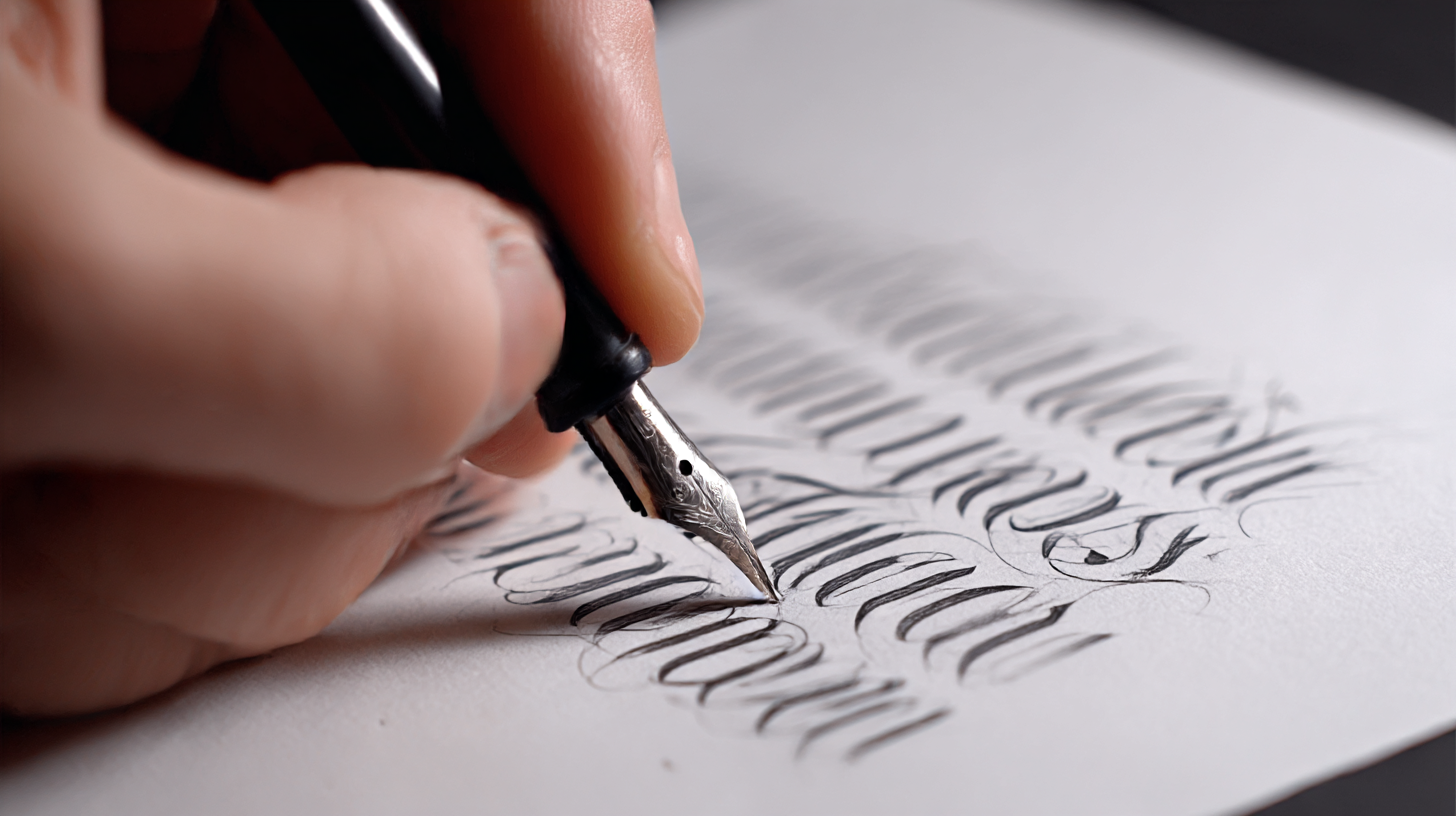
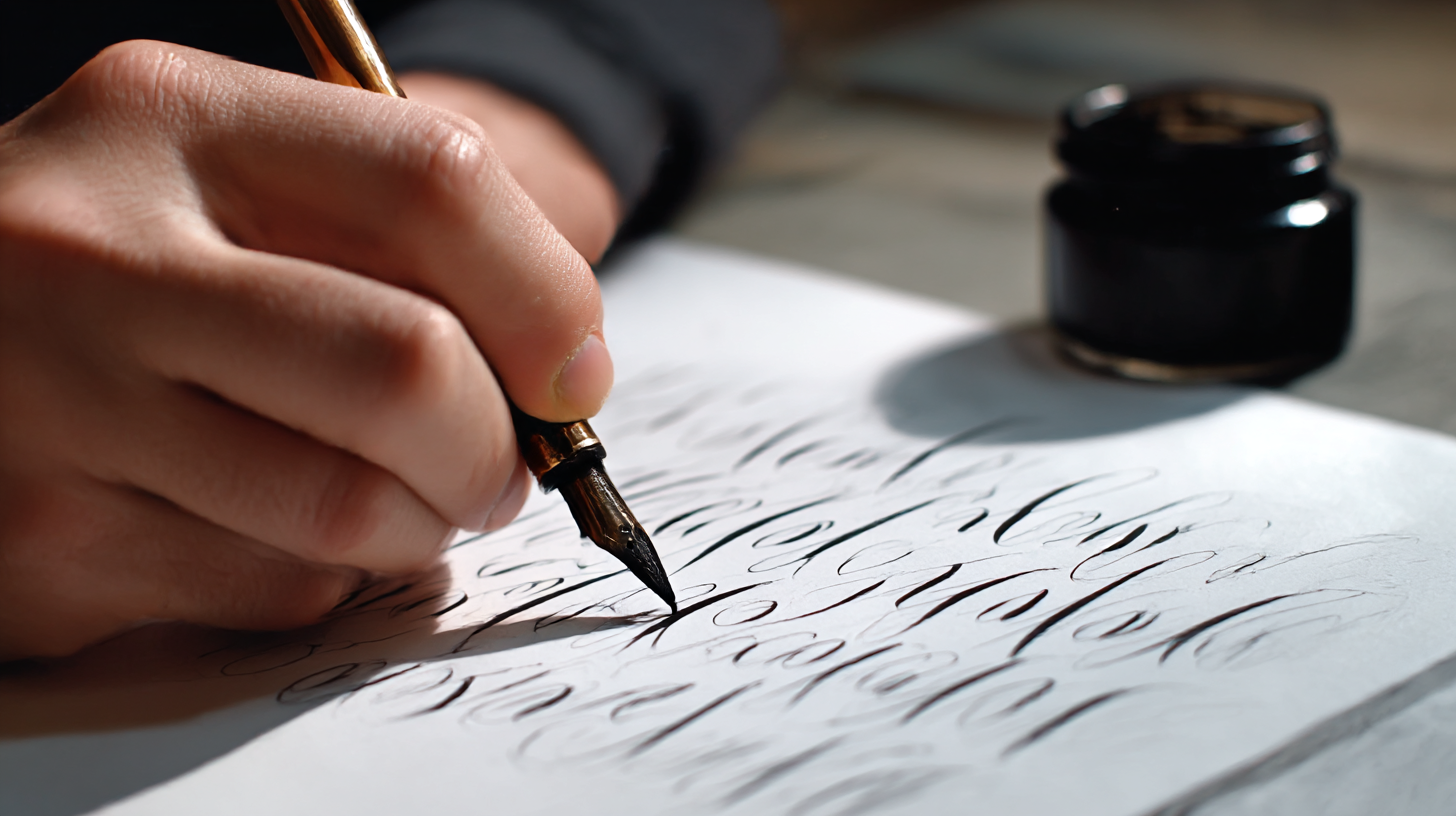
손글씨로 디자인하는 캘리그래피 기초 연습 🖌 캘리그래피(Calligraphy)는 단순한 손글씨가 아니라, 디자인적인 요소가 가미된 예술적인 글씨체예요. 감성적인 문구나 멋진 타이포그래피를 직접 만들 수 있어서 다이어리 꾸미기, 카드 디자인, 인테리어 소품 등에 많이 활용된답니다. 🎨✨
내가 생각했을 때 캘리그래피는 자신만의 개성을 담아 손글씨를 디자인하는 특별한 과정이에요. 이번 글에서는 초보자도 쉽게 따라 할 수 있는 캘리그래피 기초 연습법과 실전 팁을 알려드릴게요! 🖋🔥
먼저, 캘리그래피의 개념과 특징부터 알아볼까요? 👇
✍ 캘리그래피란?
캘리그래피(Calligraphy)는 손글씨를 활용해 디자인적인 요소를 가미한 글씨체예요. 단순한 필기가 아니라 감성을 담아 글씨를 꾸미고, 강약을 조절하며 독창적인 스타일을 표현하는 것이 특징이랍니다. 🖌✨
📌 캘리그래피의 주요 특징
특징 설명 🎨 감성적인 표현 획의 굵기와 스타일을 조절해 감각적인 디자인 연출 🖌 다양한 도구 활용 붓펜, 만년필, 브러시 마커 등 다양한 필기구 사용 가능 ✍ 필압 조절 획의 강약을 조절해 예술적인 효과 극대화 📜 다양한 용도 다이어리, 명언 필기, 카드 디자인, 로고 제작 등 활용 이처럼 캘리그래피는 단순한 손글씨를 넘어 예술적인 가치를 담을 수 있어요! 이제 캘리그래피의 다양한 글씨체 스타일을 살펴볼까요? ✨
🖋 캘리그래피 글씨체 스타일
캘리그래피는 글씨체에 따라 분위기가 완전히 달라질 수 있어요! 어떤 스타일을 선택하느냐에 따라 감성적인 느낌을 강조하거나, 개성 넘치는 디자인을 연출할 수 있답니다. ✍✨
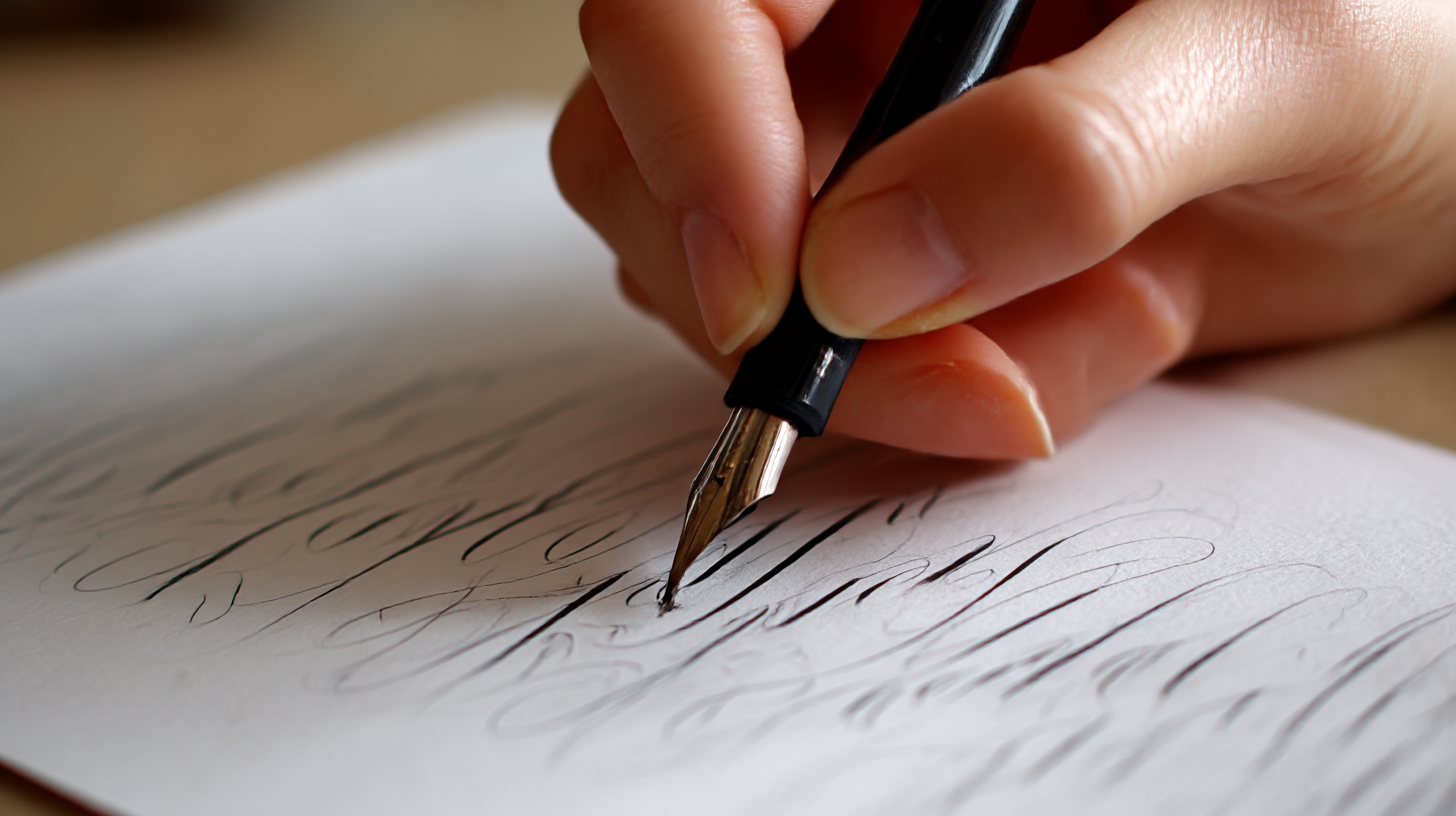
캘리그래피 글씨체 스타일 📌 대표적인 캘리그래피 글씨체 비교
글씨체 스타일 특징 추천 용도 🖊 기본 정자체 획이 일정하고 단정한 느낌 노트 필기, 명언 기록 🖌 붓펜 흘림체 부드럽고 유려한 흐름 감성 필기, 카드 디자인 🎨 브러시 캘리그래피 획의 강약이 뚜렷하고 역동적인 느낌 포스터, 로고 디자인 📝 손글씨 스타일 자연스럽고 개성적인 느낌 다이어리 꾸미기, 감성 노트 이처럼 다양한 캘리그래피 스타일 중 나에게 맞는 스타일을 선택해 연습하면 더욱 재미있어요! 이제 캘리그래피의 기초 연습법을 단계별로 배워볼까요? ✍✨
✍ 캘리그래피 기초 연습법
캘리그래피를 처음 시작하는 분들은 기본적인 선 연습부터 차근차근 연습하는 것이 중요해요! 획의 강약을 조절하고, 자연스러운 흐름을 익히면서 점차 다양한 스타일을 시도해볼 수 있답니다. 🖌✨
📌 단계별 캘리그래피 연습법
연습 단계 설명 추천 도구 1단계: 선 연습 직선, 곡선, 점선 등 다양한 선을 일정하게 그려보기 연필, 모눈 노트 2단계: 필압 조절 획의 강약을 조절하는 연습 붓펜, 브러시 마커 3단계: 알파벳 & 한글 연습 글자의 균형을 맞추며 정자체 & 흘림체 연습 만년필, 젤펜 4단계: 단어 & 문장 쓰기 자연스럽게 단어를 연결하면서 스타일 완성 브러시 펜, 마카 이 과정을 따라가면 점점 자연스럽고 멋스러운 캘리그래피가 완성될 거예요! 이제 더 개성 있는 표현을 위한 캘리그래피 기법도 알아볼까요? 🎨✨
🎨 캘리그래피 표현 기법
캘리그래피를 더 감각적으로 만들기 위해서는 다양한 표현 기법을 활용하는 것이 좋아요! 획의 강약을 조절하거나, 글자 간격을 변형하는 등의 기법을 적용하면 더욱 독창적인 스타일을 연출할 수 있답니다. ✍✨
📌 감성적인 캘리그래피 표현 기법
기법 설명 추천 도구 🖌 필압 조절 획의 굵기를 조절해 강약을 강조하는 기법 붓펜, 브러시 마커 🎭 레터 스페이싱 글자 간격을 조절해 독창적인 분위기 연출 모눈 노트, 젤펜 🔄 획 변형 획을 일부러 구부리거나 늘려서 개성을 더하는 기법 캘리그래피 펜, 마커 🌈 색상 그라데이션 두 가지 이상의 색상을 조합해 부드러운 색 변화 표현 브러시 마커, 수채화 물감 이러한 기법들을 적절히 활용하면 더욱 감성적이고 예술적인 캘리그래피를 완성할 수 있어요! 이제 캘리그래피에 적합한 도구들도 함께 알아볼까요? 🖊✨
🖊 캘리그래피 추천 도구
캘리그래피를 연습할 때는 필기감이 부드럽고 획 조절이 쉬운 도구를 사용하는 것이 중요해요! 아래에서 초보자부터 전문가까지 활용할 수 있는 다양한 캘리그래피 도구를 추천해드릴게요. ✨
📌 캘리그래피 연습에 좋은 필기구 추천
필기구 특징 추천 용도 🖋 텀보우 후데노스케 필압 조절이 쉬운 붓펜 초보자 연습, 감성 필기 🖌 펜텔 브러시펜 유연한 붓 촉으로 섬세한 표현 가능 전문적인 캘리그래피 ✏ 크레토로 만년필 필기감이 부드럽고 선명한 획 표현 가능 정자체 연습 🎨 마일드라이너 형광펜 부드러운 파스텔 색감 강조 & 꾸미기
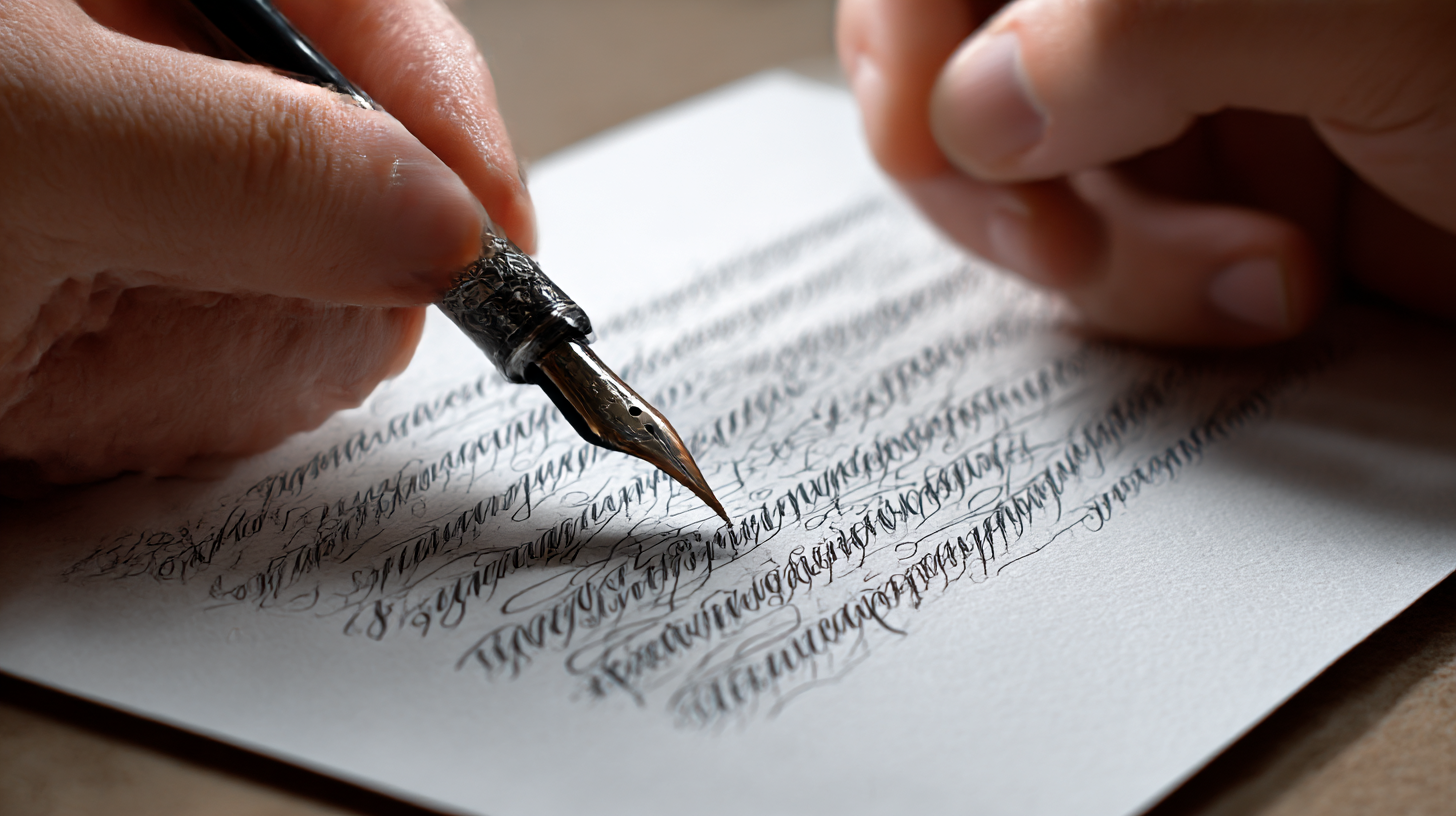
캘리그래피 추천 도구 📒 캘리그래피 연습에 적합한 노트 추천
노트 종류 특징 추천 필기 스타일 📏 모눈 노트 획 정렬 연습에 도움 정자체, 필압 연습 🟠 도트 그리드 노트 획의 균형을 잡기 쉬움 흘림체, 감성 필기 📖 무지 노트 자유로운 스타일 가능 캘리그래피 연습 이 도구들을 활용하면 캘리그래피 연습이 더욱 즐거워질 거예요! 이제 캘리그래피를 더욱 잘하는 실전 꿀팁도 함께 알아볼까요? 🖋✨
💡 캘리그래피를 잘하는 실전 꿀팁
캘리그래피는 단순한 글씨가 아니라 획의 강약과 흐름을 조절하는 예술적인 표현 방식이에요. 초보자도 쉽게 따라 할 수 있는 몇 가지 실전 꿀팁을 적용하면 더욱 감각적인 캘리그래피를 완성할 수 있답니다! ✨
📌 캘리그래피 실력을 높이는 5가지 꿀팁
꿀팁 설명 1. 필압 조절 연습 획의 강약을 주면서 굵기 차이를 조절하는 연습을 해보세요. 2. 손목 대신 팔을 움직이기 손목을 고정하고 팔 전체를 활용하면 자연스럽고 부드러운 획을 그릴 수 있어요. 3. 천천히, 그리고 리듬감 있게 너무 빨리 쓰지 말고, 일정한 속도로 글씨를 써보세요. 리듬감 있는 필기가 중요해요! 4. 글자 간격 & 정렬 맞추기 균형 잡힌 글씨를 위해 글자 간격과 정렬을 신경 써 보세요. 5. 다양한 도구로 연습하기 붓펜, 만년필, 브러시 마커 등 다양한 필기구를 사용해보면서 나에게 맞는 도구를 찾아보세요. 이 팁들을 적용하면 더욱 세련된 캘리그래피 스타일을 완성할 수 있어요! 이제 캘리그래피와 관련된 자주 묻는 질문(FAQ)을 확인해볼까요? 🤔
Q1. 캘리그래피를 처음 배우는데 어떤 도구를 사용하면 좋을까요?
A1. 초보자는 텀보우 후데노스케 붓펜이나 펜텔 브러시펜이 사용하기 쉬워요! 처음에는 연필이나 젤펜으로 필압 조절 연습을 한 후, 붓펜으로 넘어가면 더욱 효과적이에요. 🖊✨
Q2. 캘리그래피를 연습할 때 하루에 얼마나 해야 실력이 늘까요?
A2. 하루 10~15분 정도라도 꾸준히 연습하는 것이 중요해요. 짧더라도 매일 연습하면 손에 익숙해져 자연스럽게 글씨가 발전한답니다. ✍
Q3. 필압 조절이 잘 안 되는데 해결 방법이 있나요?
A3. 먼저 가벼운 힘으로 선을 긋는 연습을 해보세요. 천천히 눌렀다 떼는 느낌으로 연습하면 점점 손에 익숙해질 거예요. 🖌
Q4. 캘리그래피에 어울리는 글씨체를 찾는 방법은?
A4. 다양한 캘리그래피 스타일을 시도해보고, 본인이 쓰기 편하고 감성이 맞는 스타일을 선택하는 것이 좋아요. 처음에는 정자체를 연습한 후, 점차 흘림체나 브러시 스타일로 발전시켜 보세요. 🎨
Q5. 캘리그래피를 디지털로 연습하고 싶은데, 어떤 프로그램을 사용하면 좋을까요?
A5. 태블릿이 있다면 프로크리에이트(Procreate)나 어도비 프레스코(Adobe Fresco)를 추천해요. 브러시 설정이 가능해서 다양한 필기 스타일을 연습할 수 있어요! 💻🖋
Q6. 캘리그래피를 할 때 글자가 삐뚤어지지 않게 쓰는 방법은?
A6. 모눈 노트나 도트 그리드 노트를 활용하면 글씨의 정렬을 맞추는 데 도움이 돼요! 또한, 처음에는 연필로 가이드라인을 그려놓고 연습하는 것도 좋은 방법이에요. 📏✨
Q7. 캘리그래피 작품을 만들 때 색상을 조합하는 방법이 있나요?
A7. 기본적으로 두 가지 색상을 메인으로 사용하고, 포인트 컬러 하나를 추가하면 조화로운 느낌이 나요. 부드러운 분위기를 원하면 파스텔톤, 강렬한 느낌을 원하면 보색 대비를 활용해 보세요! 🎨🌈
Q8. 캘리그래피를 활용할 수 있는 실용적인 방법은?
A8. 다이어리 꾸미기, 명언 기록, 카드 디자인, 포스터 제작, 인테리어 액자 등 다양한 활용이 가능해요! 특히 핸드메이드 카드나 감성적인 문구를 적으면 더욱 의미 있는 작품이 된답니다. 🖌📜